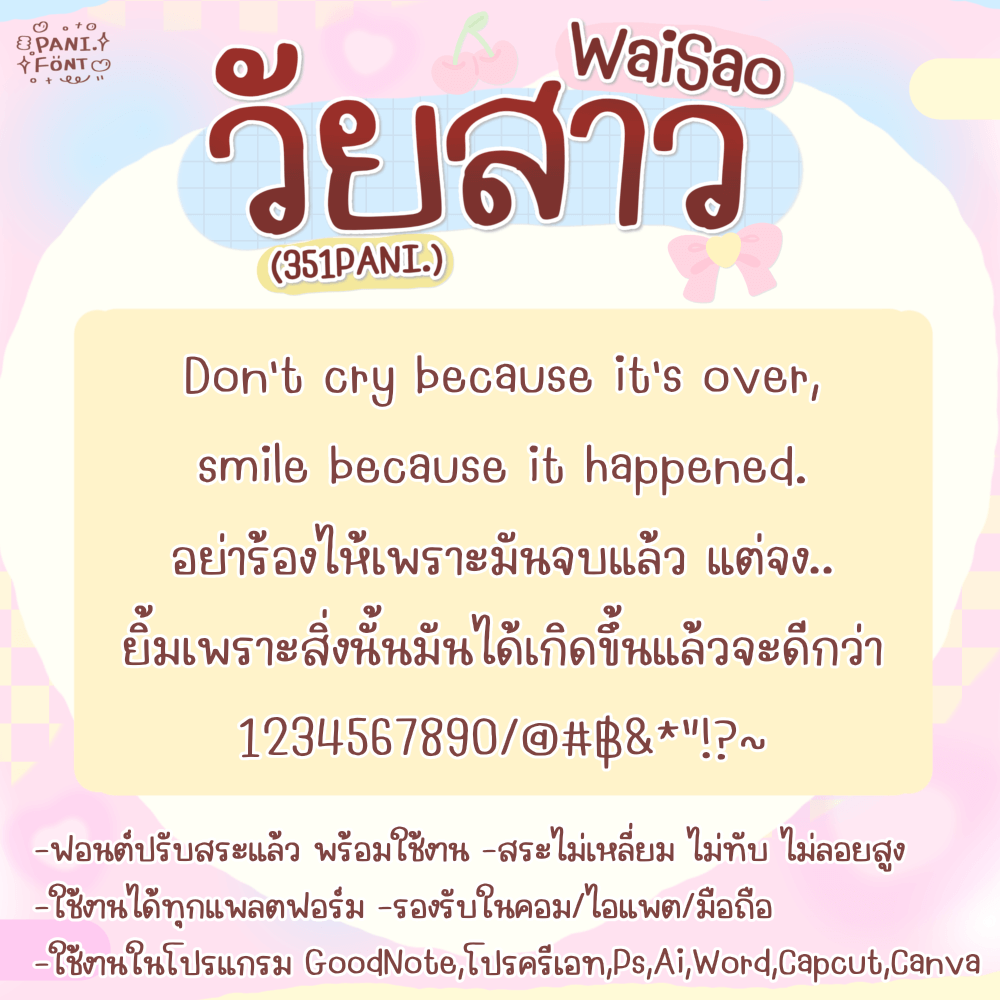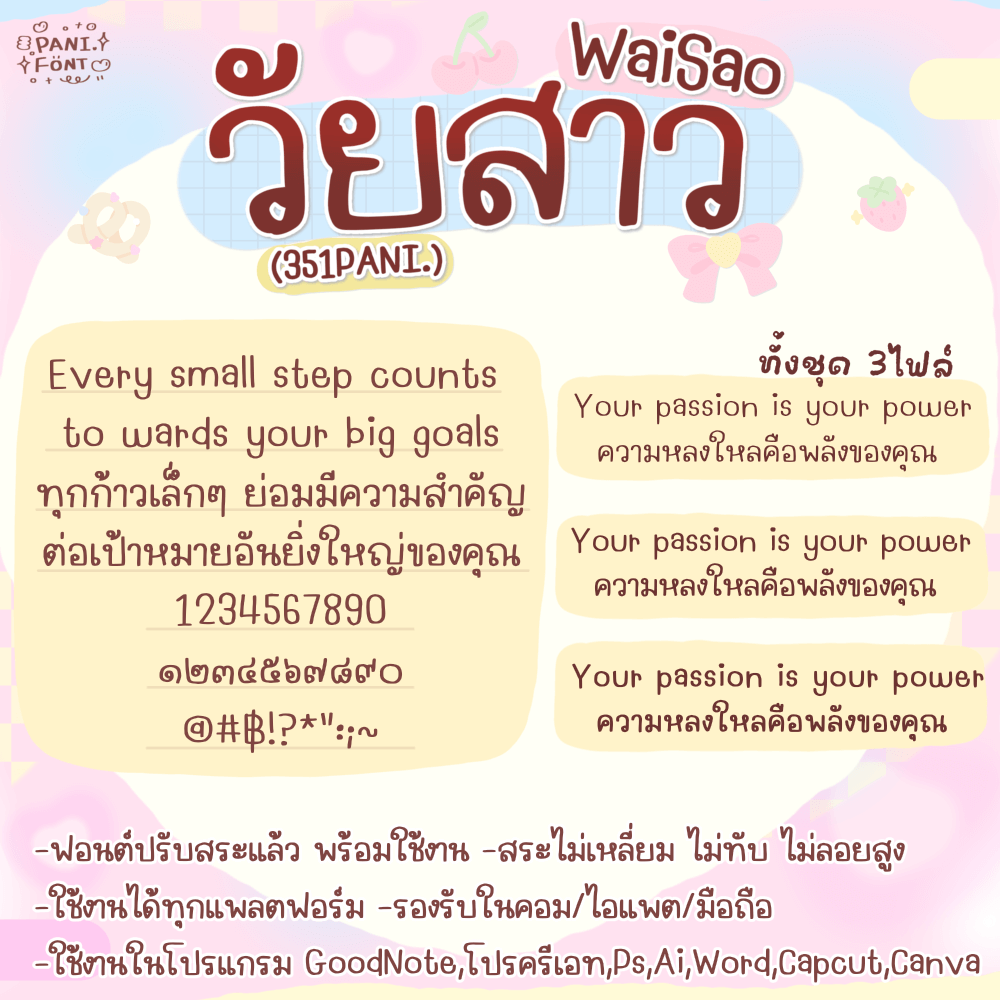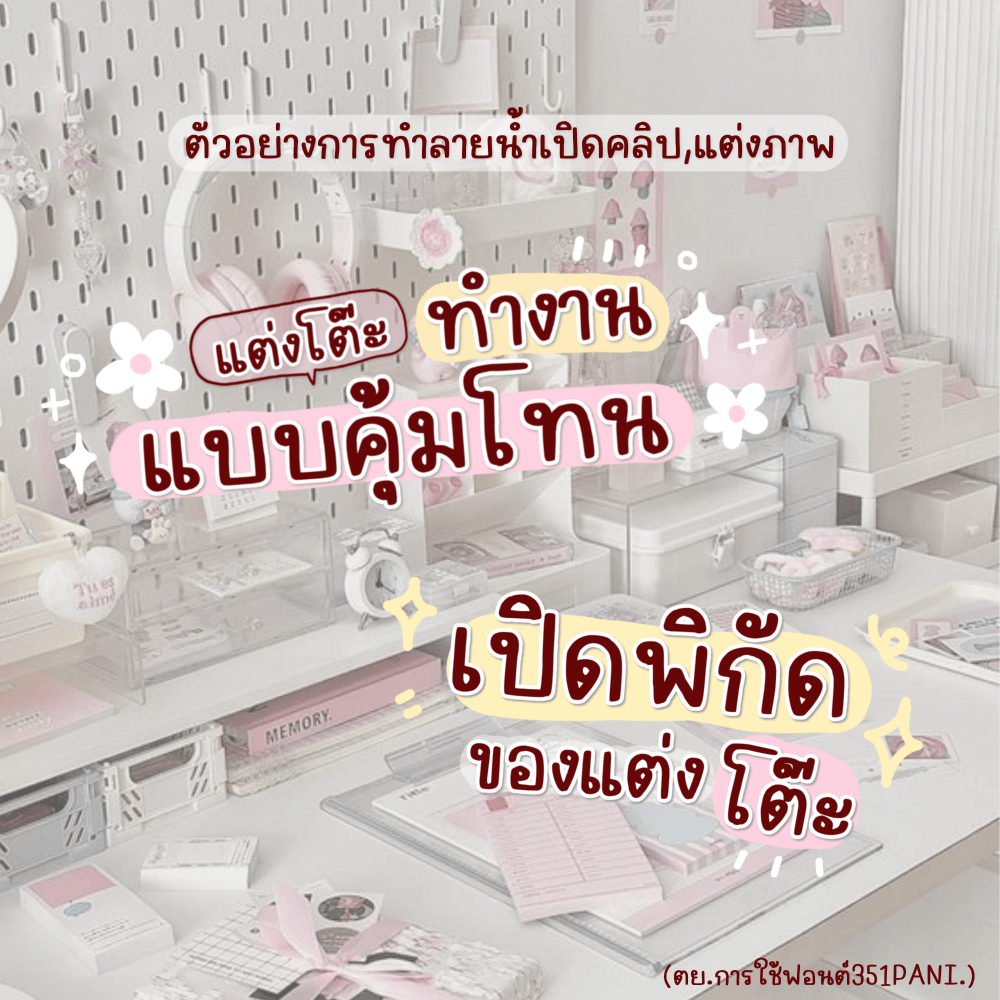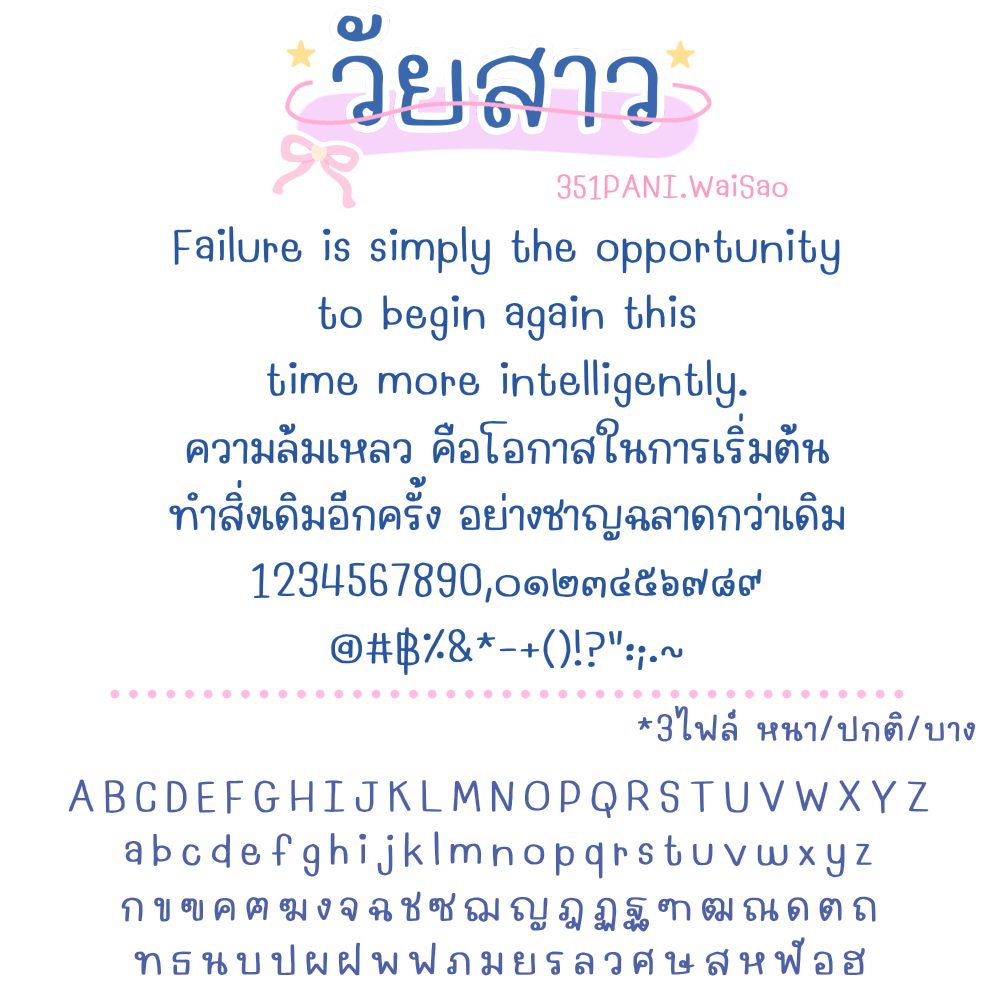
351PANI.วัยสาว
ฟอนต์ 351PANI.วัยสาว – ฟอนต์แนวเรียบร้อย อ่านง่าย สบายตา เหมาะกับการใช้งานได้หลากหลาย จดโน้ต อ่านรายละเอียด ทำหัวคลิปสวย เป็นแนวฟอนต์คู่ควรมีติดคลังเลยค่ะ ใครชอบแนวเรียบร้อย แนะนำเลยค่า